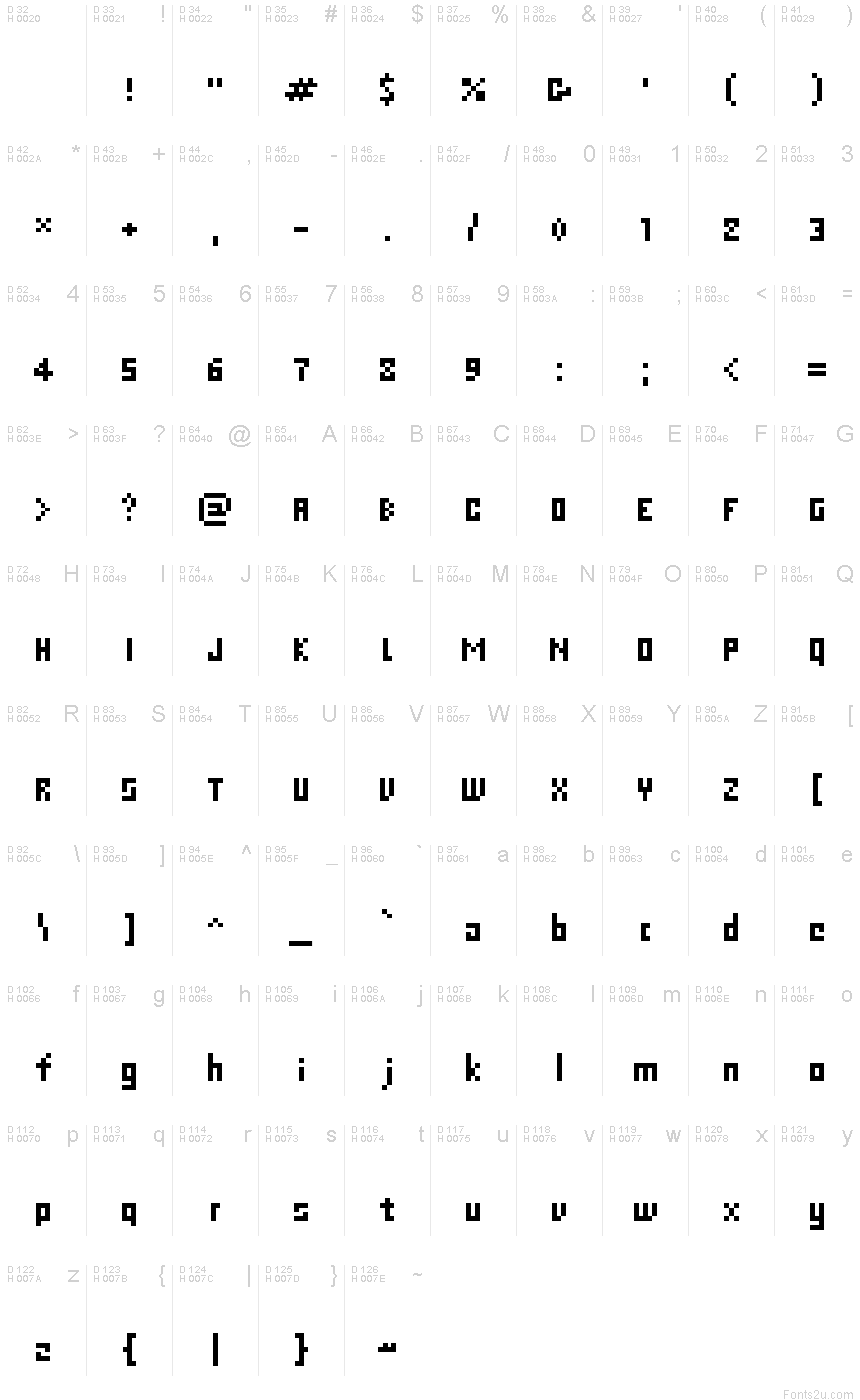
C Web Small von Andreas Carlsson ist eine kostenlose Bitmap-Pixel-Schriftart aus der C Web-Familie. Sie ist in knackigen, blockartigen Quadraten gestaltet, die wie 1-Bit-Tinte auf alten Bildschirmen wirken. Ihr kompakter Rhythmus und die markanten Ecken sorgen auch bei wenig Platz für ein knackiges Schriftbild – perfekt für den Look von Vintage-Browsern oder Handheld-Konsolen.
C Web Small eignet sich hervorragend für Game-HUDs, Pixel-Art-Titel, UI-Labels, Retro-Tech-Poster, Zines, Album-Cover, App-Icons und glitchige Social-Media-Grafiken. Verwenden Sie die Schrift vorzugsweise in kleinen Größen mit etwas mehr Zeilenabstand, damit die Pixel zur Geltung kommen, und kombinieren Sie diese kostenlose Schriftart für längere Texte mit einer neutralen serifenlosen Schrift.